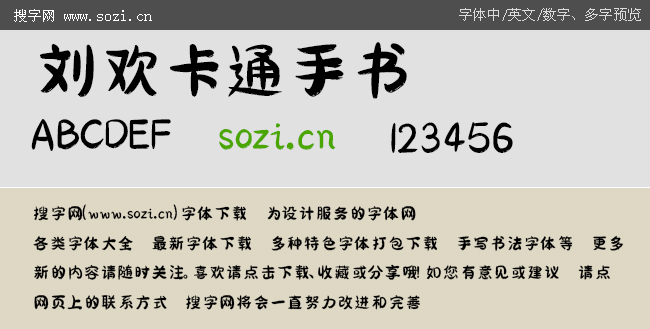
劉歡卡通手書(shū)
搜字網(wǎng)給大家提供一款劉歡卡通手書(shū)中文字體下載,劉歡卡通手書(shū)字體是一款揉合了傳統(tǒng)意味的現(xiàn)代字體,所有筆畫(huà)以“圓潤(rùn)”為主,保留少量飛白,字體整潔干練,筆畫(huà)筆順之間的銜接十分連貫。適用于海報(bào)設(shè)計(jì)、包裝設(shè)計(jì)、廣告設(shè)計(jì)等場(chǎng)景。